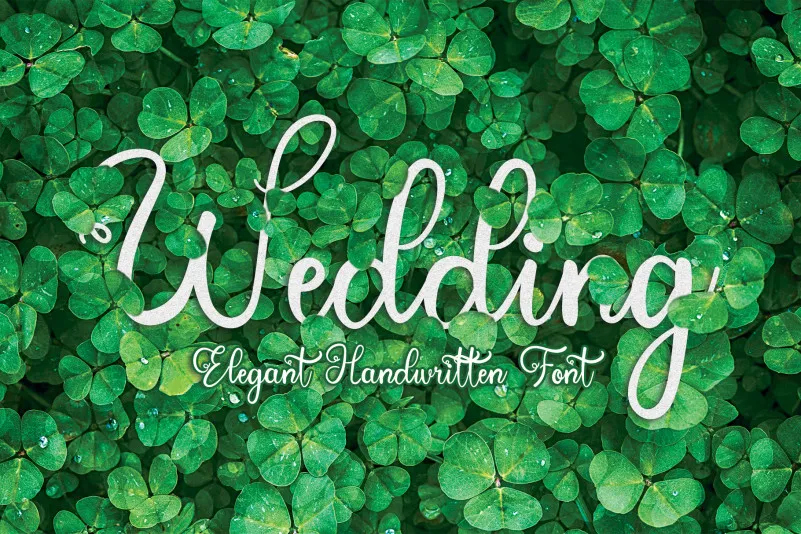
Wedding Calligraphy Font – Download Grátis
Esta fonte de escrita manual é uma criação delicada e fluida que manterá sua beleza clássica enquanto mantém um toque contemporâneo e fresco. Ela será perfeita para aqueles projetos artísticos e decorativos, seja para adicionar um charme especial a cartões de aniversário ou convites de casamento. Esta fonte traz vida e amor ao seu trabalho, ajudando-o a alcançar altos níveis em qualquer projeto que faça. Seja você uma estilista, designer gráfico, ilustrador ou até mesmo um criativo usando o computador para criar arte digital, essa fonte de escrita manual é sua melhor aliada. Descubra como ela pode transformar a maneira como você expressa suas ideias e dá vida aos seus projetos!